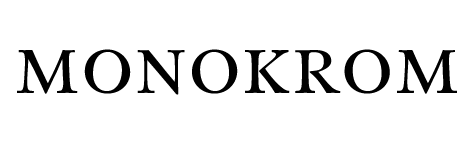
• Land: Norwegen
• Ort: Birkeland
• Gegründet: 2012
Monokrom ist eine unabhängige Schriftschmiede in Norwegen, welche von Frode Helland und Sindre Bremnes gegründet wurde. Ihr Ziel ist es, hochwertige und einzigartige Schiften mit nordischem Charakter anzubieten.